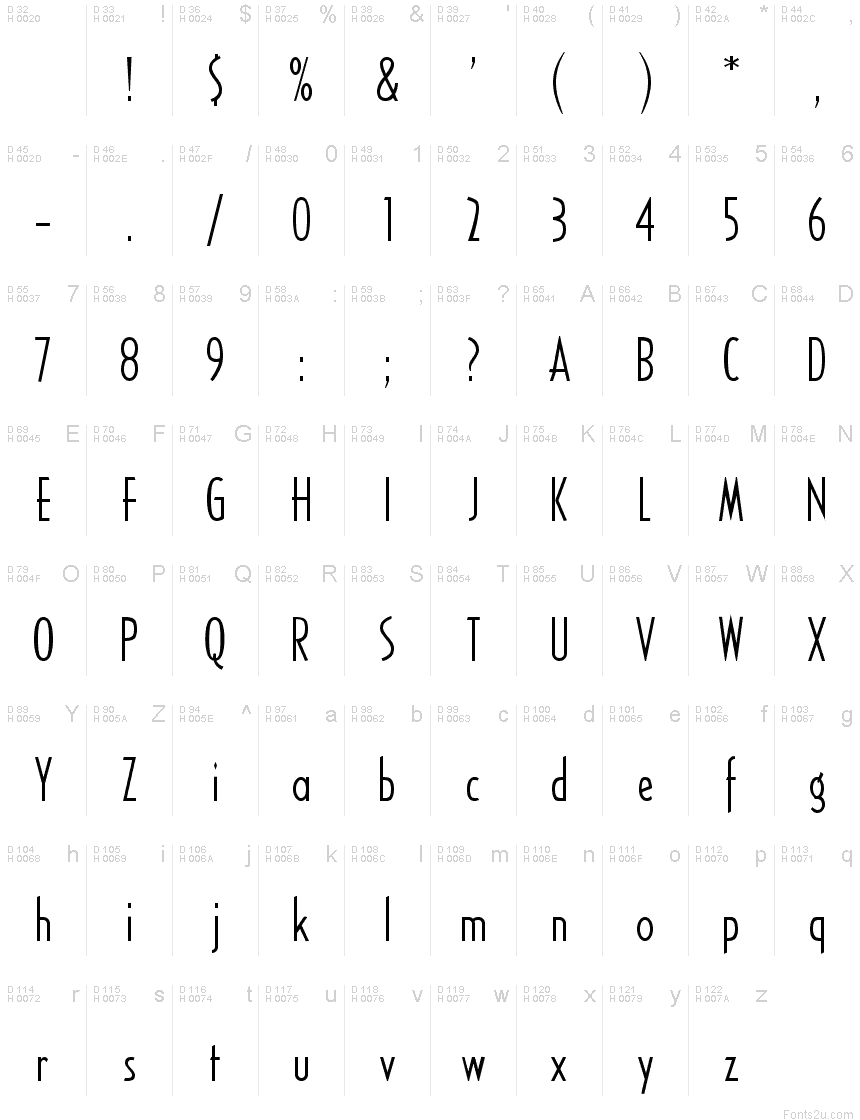
Cassandra to bezpłatny, dekoracyjny krój bezszeryfowy o wysokich, smukłych proporcjach. Dzięki eleganckim pionowym liniom i miękkim, zaokrąglonym kształtom, litery wydają się niemal odręcznie rysowane. Znaki są zestawione blisko siebie, co tworzy elegancki, rytmiczny układ, a subtelne krzywizny sprawiają, że krój nie wydaje się surowy ani mechaniczny. Efektem jest oryginalny styl z nutą art déco – wyrafinowany, a zarazem przystępny, przypominający szyldy stylowych kawiarni czy butików.
Dzięki swojej wąskiej formie Cassandra oszczędza miejsce, nie tracąc przy tym charakteru, co czyni ten bezpłatny font naturalnym wyborem do plakatów, okładek książek, zaproszeń, logotypów, opakowań oraz nagłówków na stronach internetowych. Najlepiej prezentuje się w dużym rozmiarze, gdzie charakterystyczne łuki i smukłe proporcje mogą w pełni wybrzmieć. Aby uzyskać harmonijne zestawienie, użyj kroju Cassandra w tytułach, łącząc go z czystym, geometrycznym krojem bezszeryfowym w tekście głównym, co zapewni czytelność i równowagę projektu.